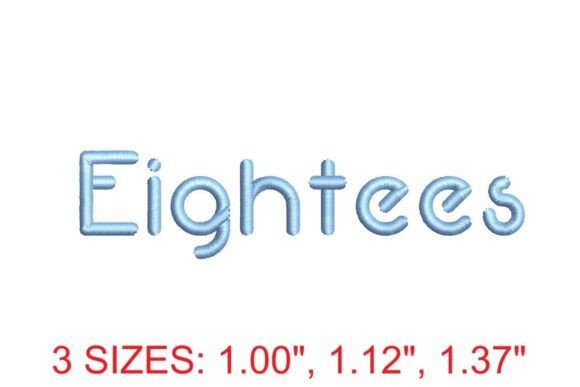
Eightees Embroidery Font
«Eightees Embroidery Font» — це винятково стилізований, машинно-готовий шрифт для вишивальних пристроїв, розроблений спеціально для тих, хто цінує ретро-естетику 1980-х у сучасному цифровому виконанні. З його чіткими контурами, добре продуманими міжлітерними відступами та оптимізованими стежками вишивки цей шрифт забезпечує бездоганне відтворення навіть на складних тканинах — від бавовни до трикотажу. Він не просто передає стиль епохи, а й працює як професійний інструмент, що зменшує ризики обриву ниток, зсуву матеріалу чи перегріву машини.
Якість збірки та технічні деталі
Шрифт надається у форматах PES, DST, EXP, JEF та VP3 — повна сумісність з усіма популярними вишивальними машинами (напр., Brother, Janome, Bernina, Tajima). Кожен символ має точну кількість стежок (в середньому 120–180 стежок на літеру), оптимізовану для мінімального витрати ниток і максимальної гладкості контурів. Висота символів — від 0,8 до 5,0 см (регульована масштабуванням без втрати якості), а всі букви включають автоматичні підстопорні стежки та плавні переходи між елементами. Поставляється разом із PDF-посібником з налаштування параметрів для різних типів тканин і ниток.
Для кого найкраще підходить цей продукт?
Цей шрифт ідеально підходить для професійних вишивальників, дрібних швейних студій та дизайнерів, що спеціалізуються на брендованій продукції, мерчі, вітальними відкритками або тематичними подарунками. Також він стане знахідкою для хобі-користувачів, які хочуть додати нотку ностальгічного шарму своїм проектам без потреби в ручній корекції файлів — завдяки вбудованим технічним оптимізаціям Eightees працює «з коробки» навіть на бюджетних машинах.
Як це порівнюється з конкурентами
На відміну від загальних вільних шрифтів (напр., «Retro Stitch» або «Vintage Script»), Eightees має спеціалізовану структуру стежок з підтримкою автоматичної компенсації розтягу тканини, що різко знижує кількість правок у Wilcom або Pulse. Порівняно з комерційними аналогами (напр., «EmbroiderEasy 80s Collection»), Eightees пропонує ширшу сумісність форматів, детальніший PDF-гайд і меншу кількість стежок при збереженні читабельності — що критично важливо для дрібних написів на дитячому одязі або аксесуарах.